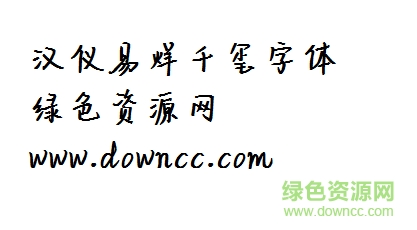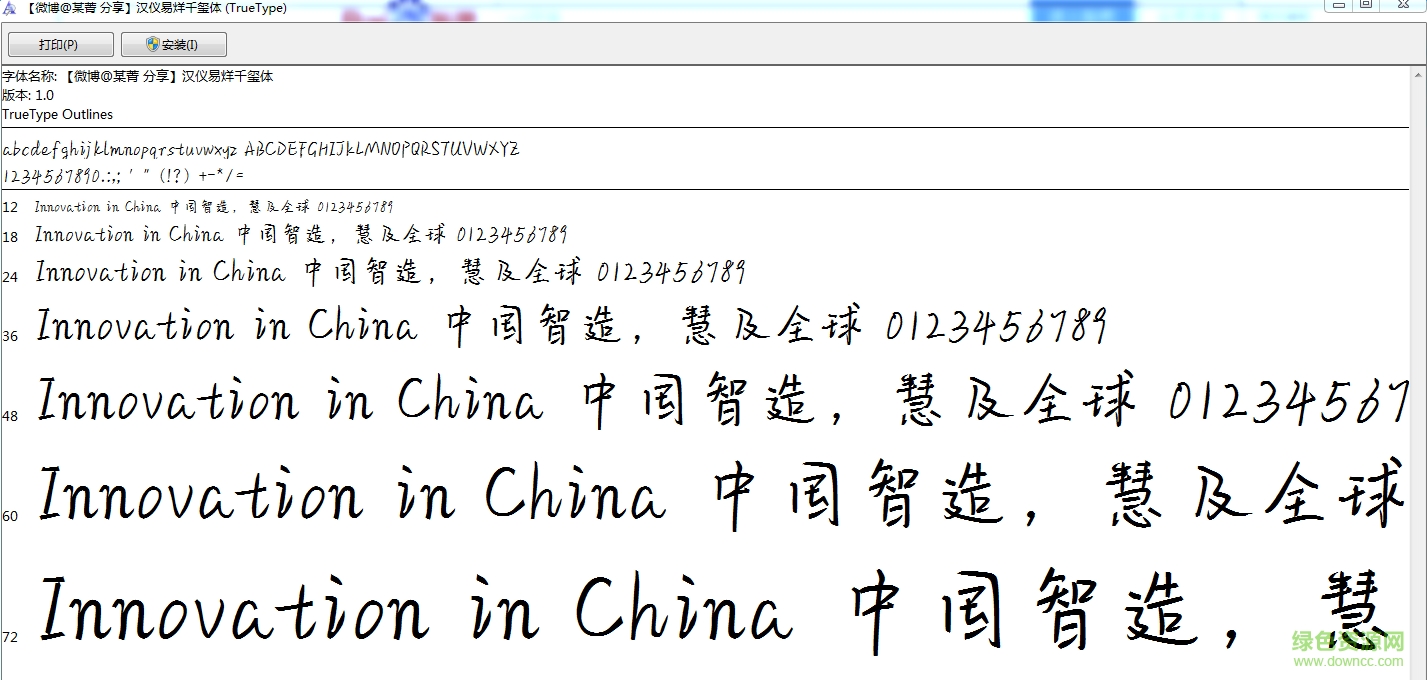
漢儀易烊千璽字體是一款漢儀類易烊千璽字體軟件,易烊千璽的字體給人非常大氣的感覺,深受廣大年輕人的喜愛,尤其是妹子們,還有更多好看字體盡情期待,歡迎到綠色資源網(wǎng)下載體驗(yàn)!
綠色資源網(wǎng)提供一款漢儀易烊千璽體手機(jī)中文字體下載,漢儀易烊千璽體是一款根據(jù)TF-boys成員易烊千璽體手寫字體制作的名人字體,易烊千璽體橫平豎直,并且剛勁有力,清秀而大氣,整體效果非常出色!